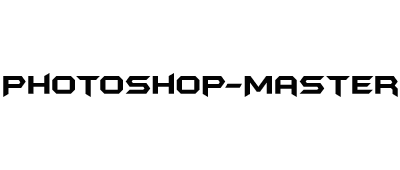
Так и не нашёл русский шрифт.. Может кто знает, где можно этот шрифт найти на русском?
Очень хороший шрифт,всем советую,особенно с неоновым стилем)Хорошо для аватарок в контакте)
Ахах) Давно его искала :D
О то - что нужно!
Афигенский шрифт!! *__*
Шрифт не очень ((
ага круть
Класный шрифт просто супер !!!!!!...